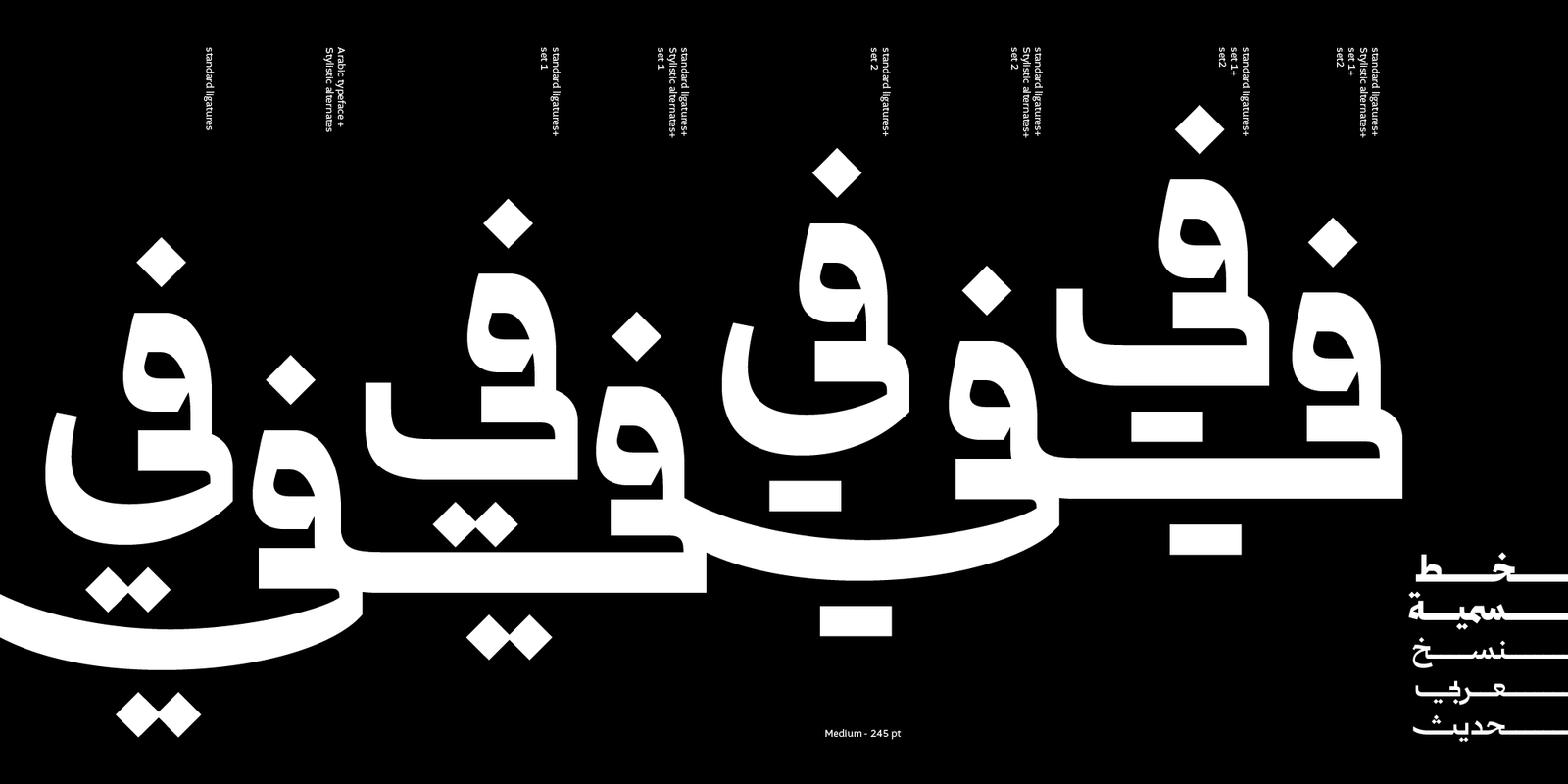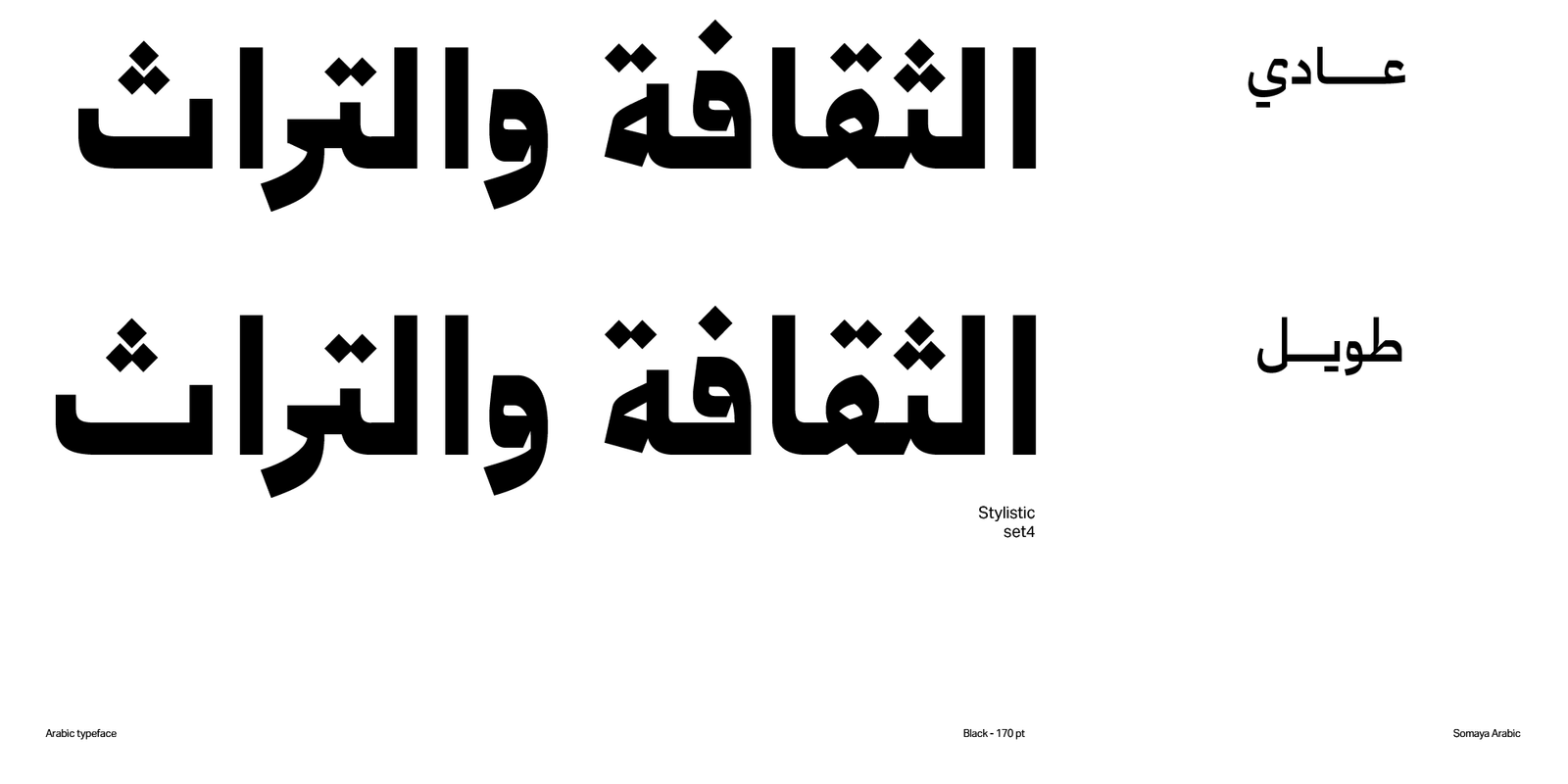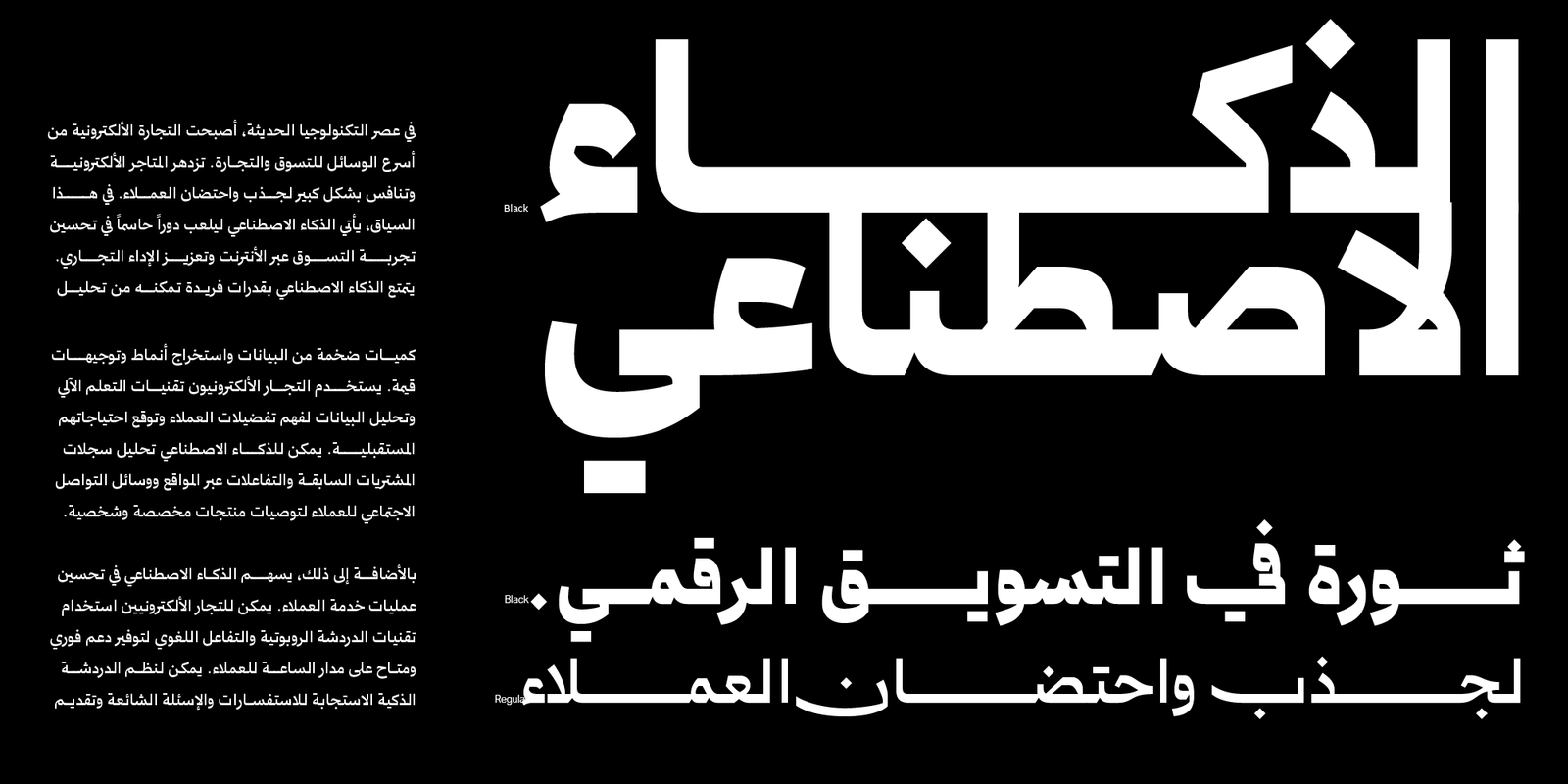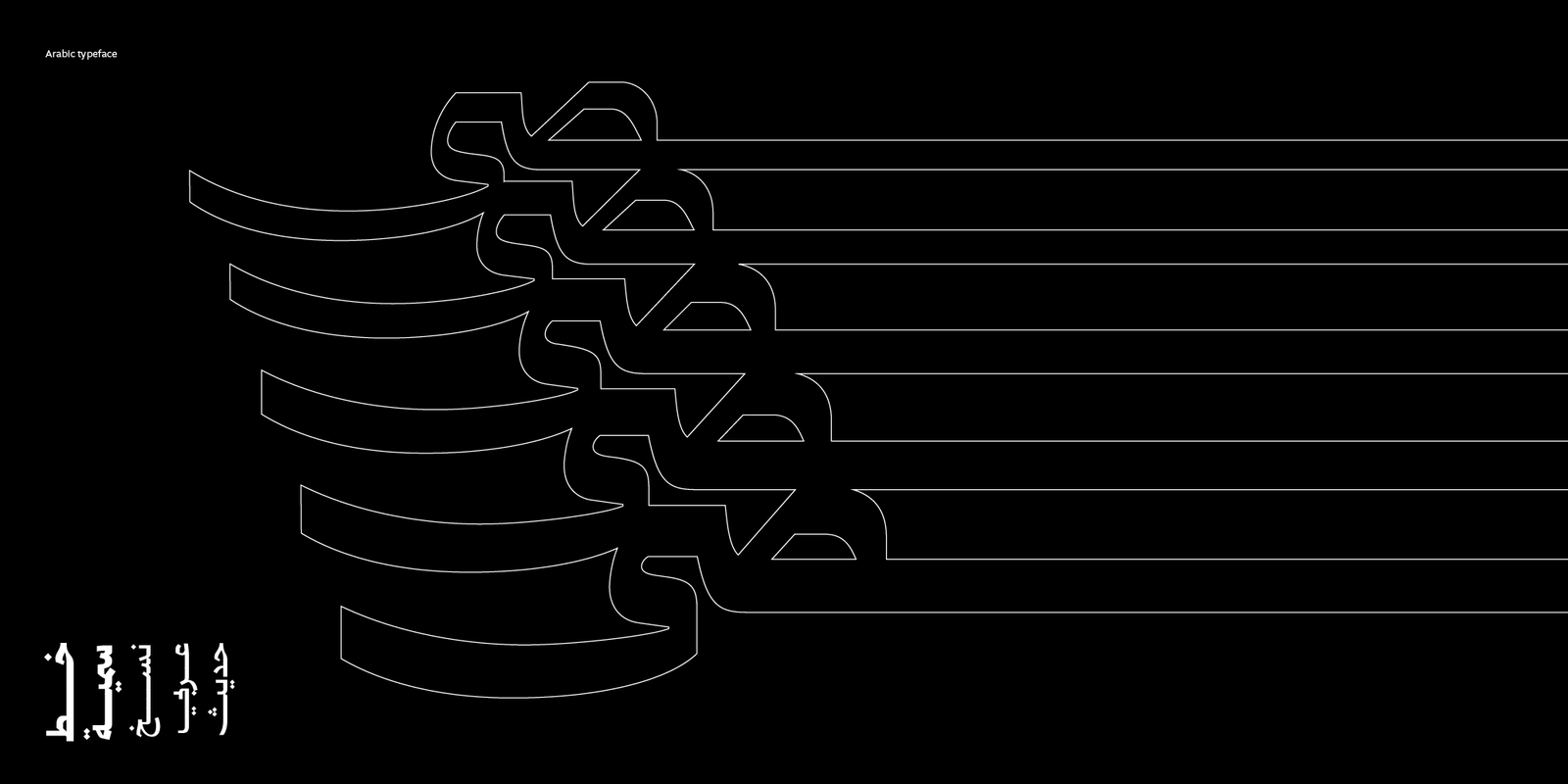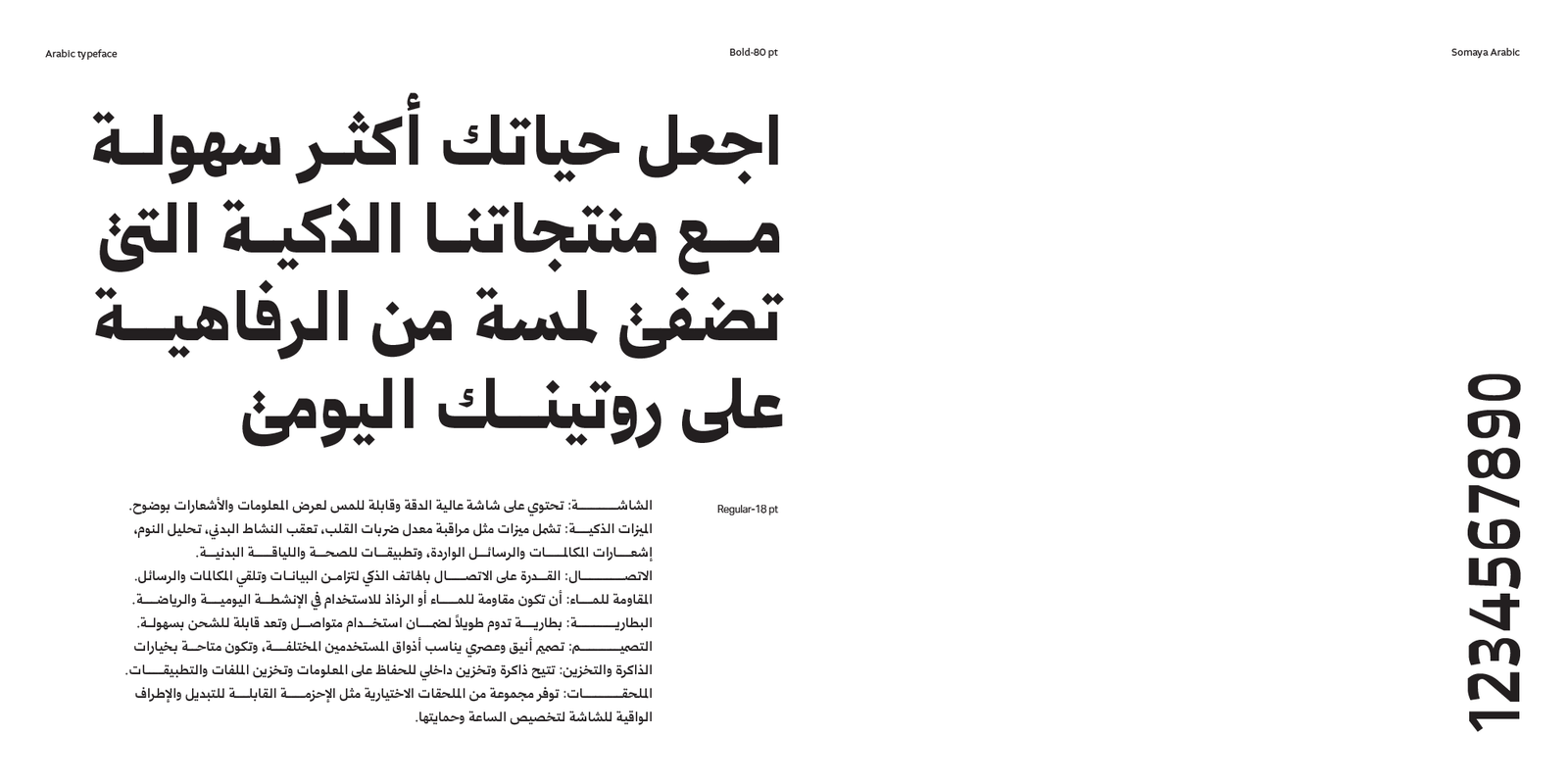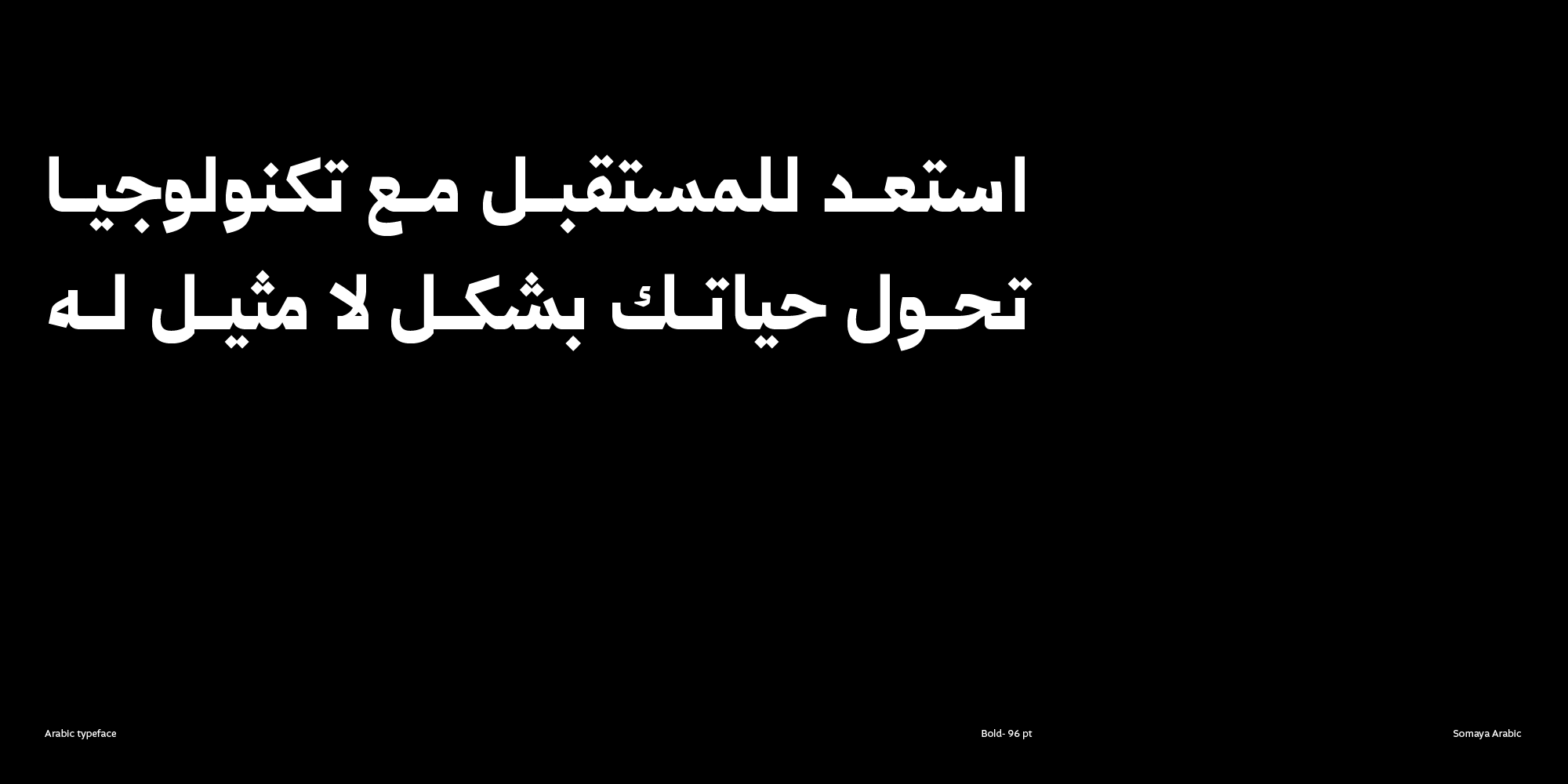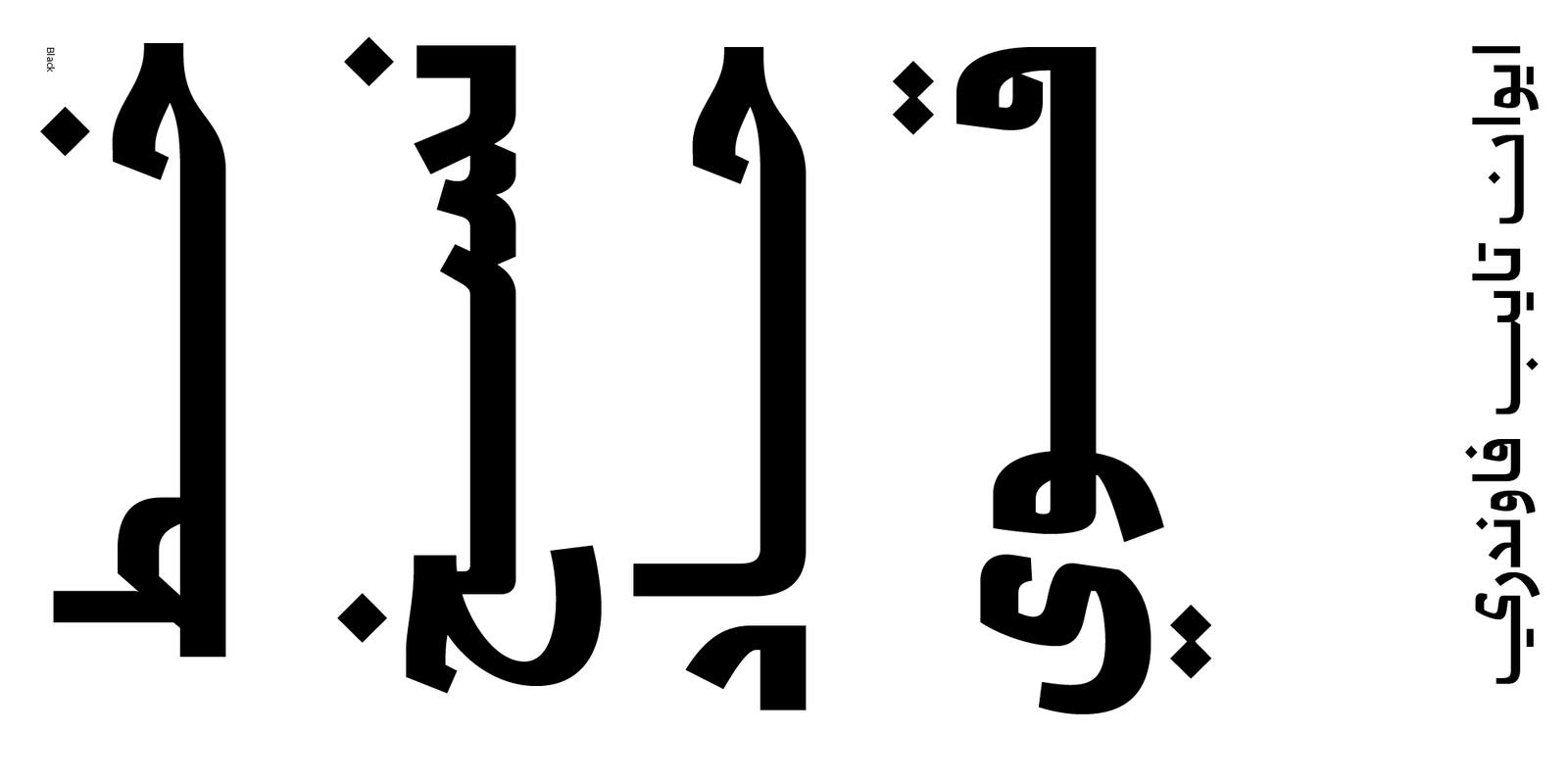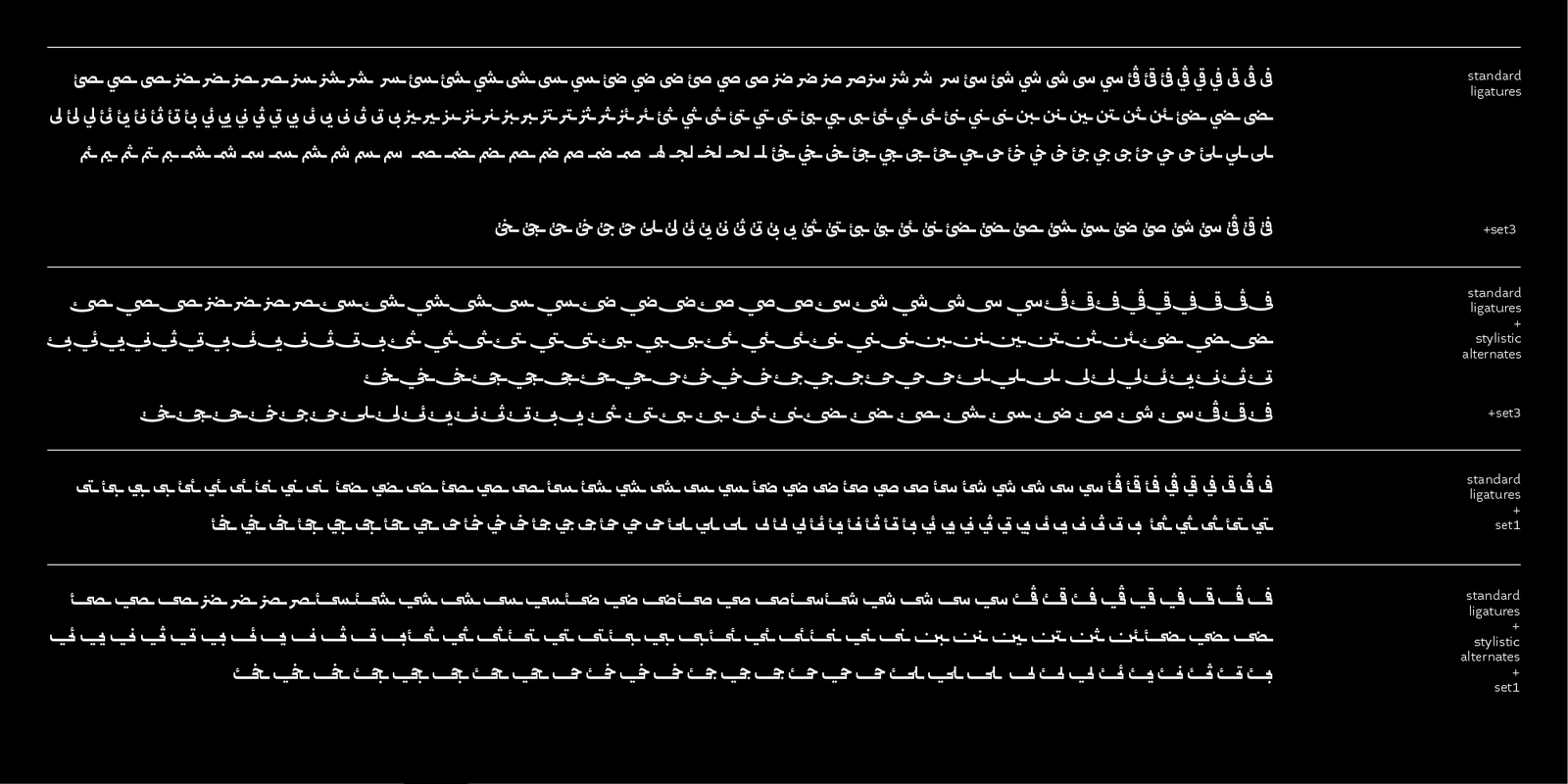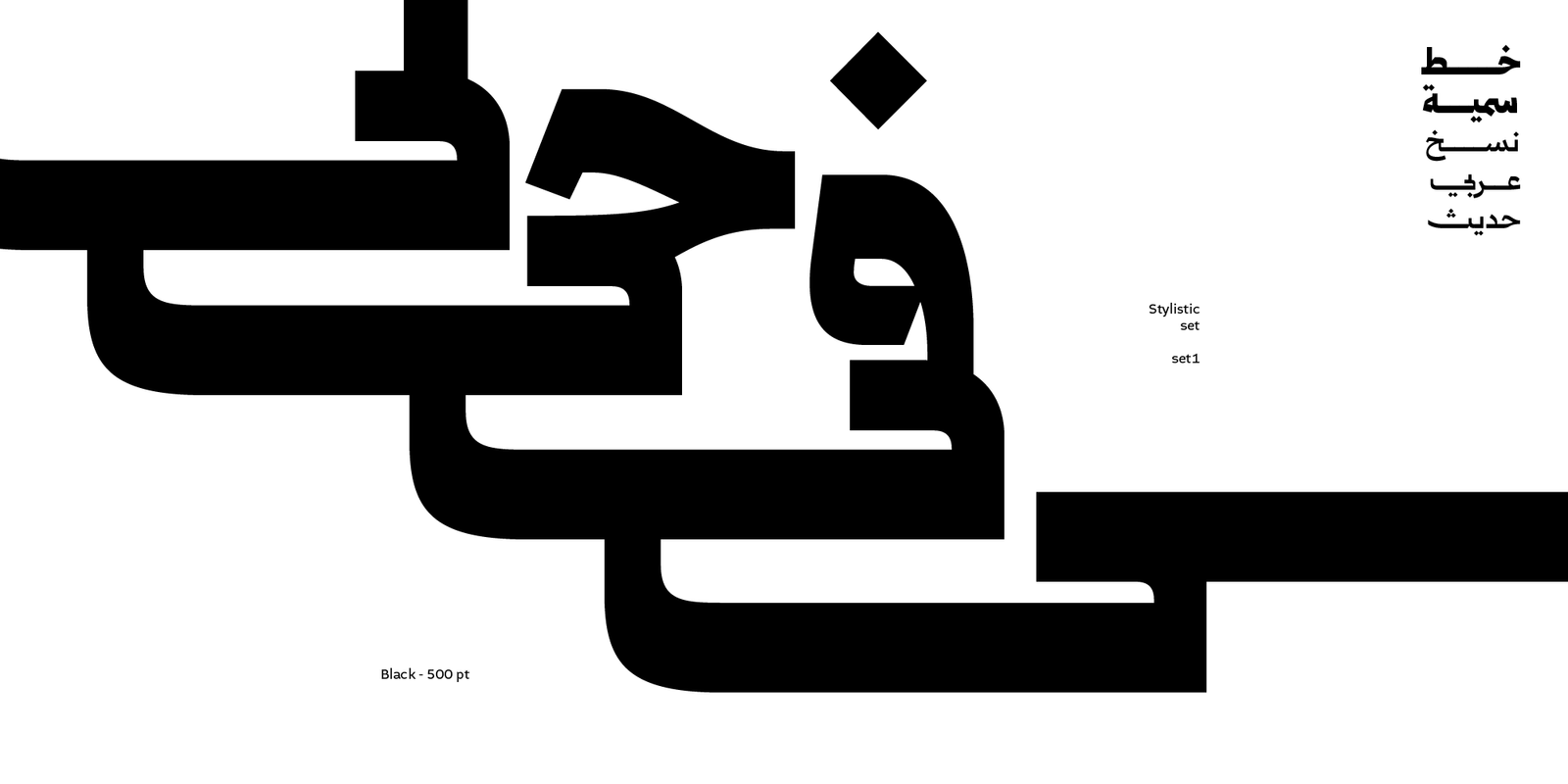
Somaya Arabic typeface – خط سمية عربي
سمية عربي هو خط طباعي عربي حديث يعكس جمال وتناغم التصميم. يتأثر التصميم بأسلوب خط النسخ العربي،
حيث يمزج بين النسخ التقليدي والحديث، مما يجعله خيارًا مثاليًا لمختلف مجالات التصميم.
يتميز خط سمية بالعديد من مميزات OpenType التي تعزز إمكانيات التصميم، منها:
الاحرف البديلة : يقدم الخط أشكالًا بديلة للحروف، مما يمكن المستخدمين من تجربة مظاهر مختلفة للنص وإضفاء لمسات شخصية.
الاحرف المرسلة:يقدم الخط أحرف مرسلة ونوعان منها
الاحرف المركبة : يتيح الخط استخدام ربط الحروف لتحسين تجربة القراءة والمظهر العام للنص.
نزول أقل : يقدم الخط أحرف بديلة لنزول اقل
الاحرف الطويلة : يقدم الخط احرف بديلة طويلةيتميز الخط بخمسة أوزان مختلفة تتراوح من الخفيف إلى الأسود،
مما يتيح للمستخدمين اختيار الوزن المناسب لمشروعهم.يُعتبر سمية عربي خيارًا مثاليًا لمجموعة واسعة من التطبيقات،
بما في ذلك التصميم الشخصي، والتحرير، والتغليف، والإعلان.
اللغات: العربية فقط، بلا حروف لاتينية
الاوزان : خمسة اوزان